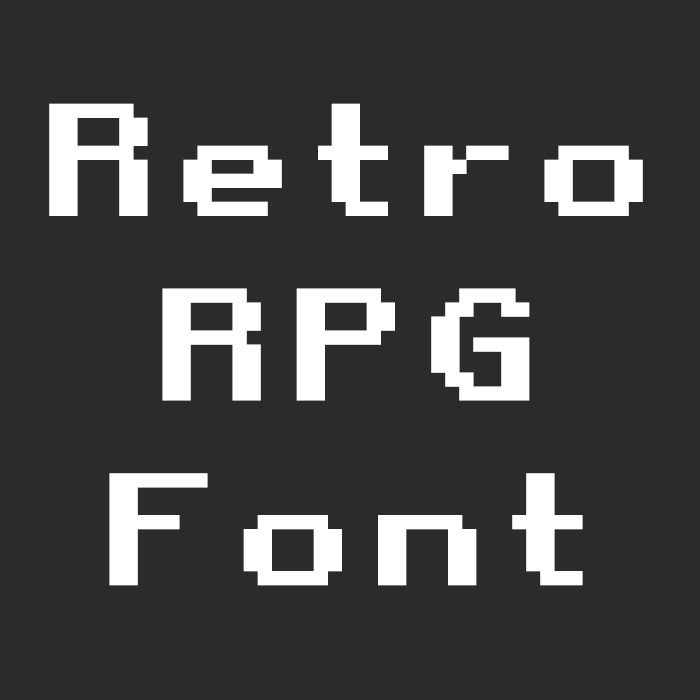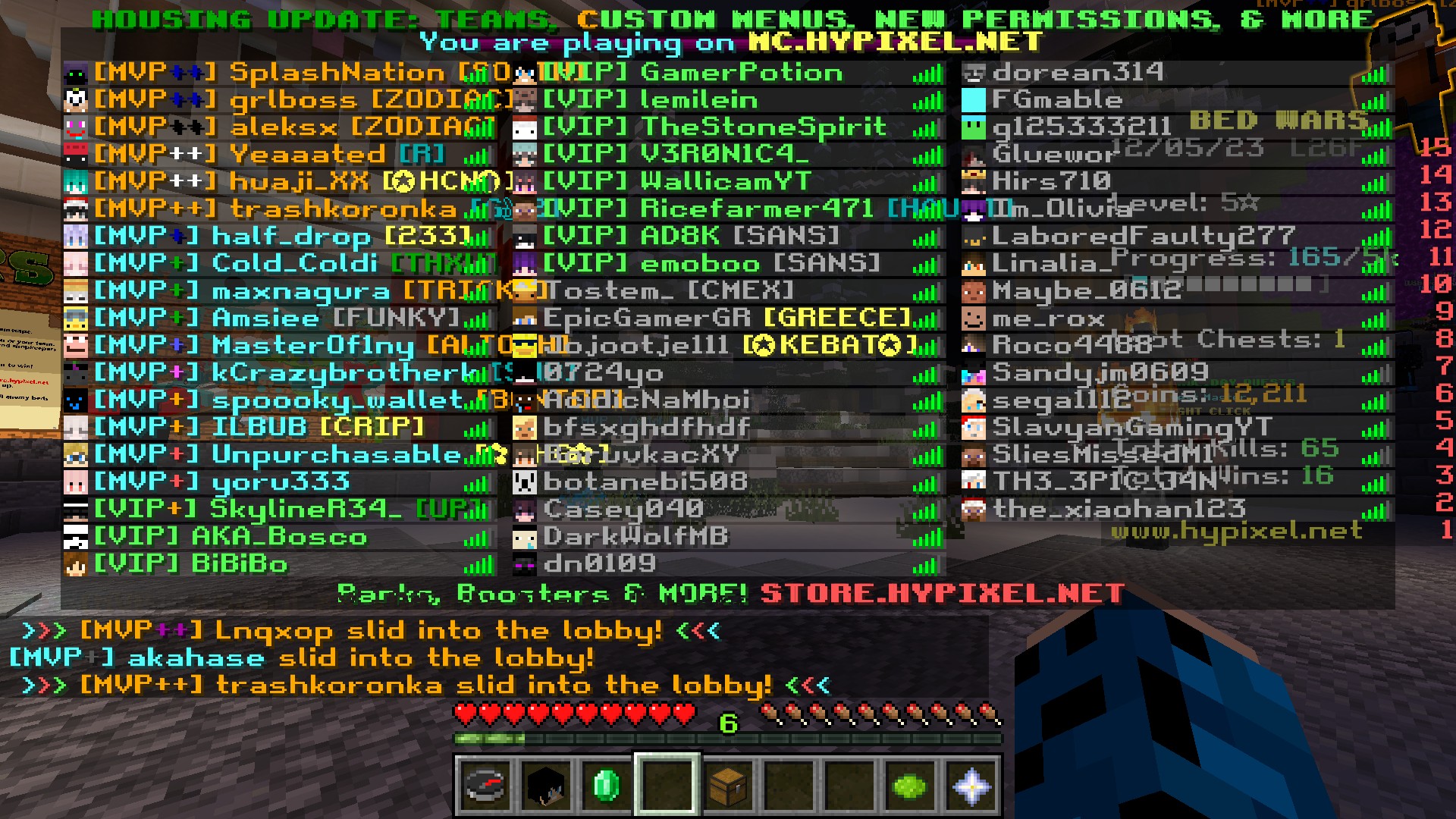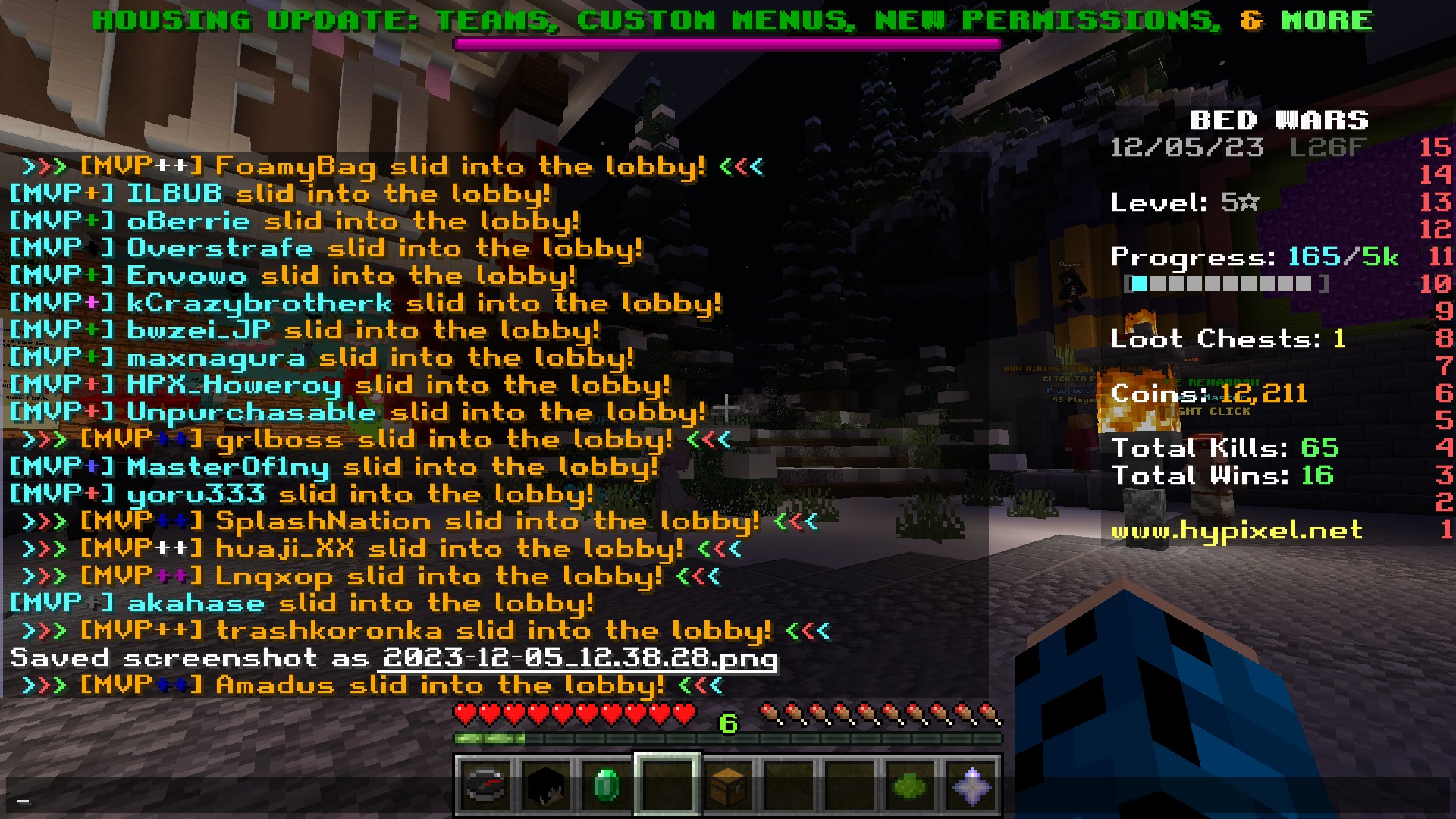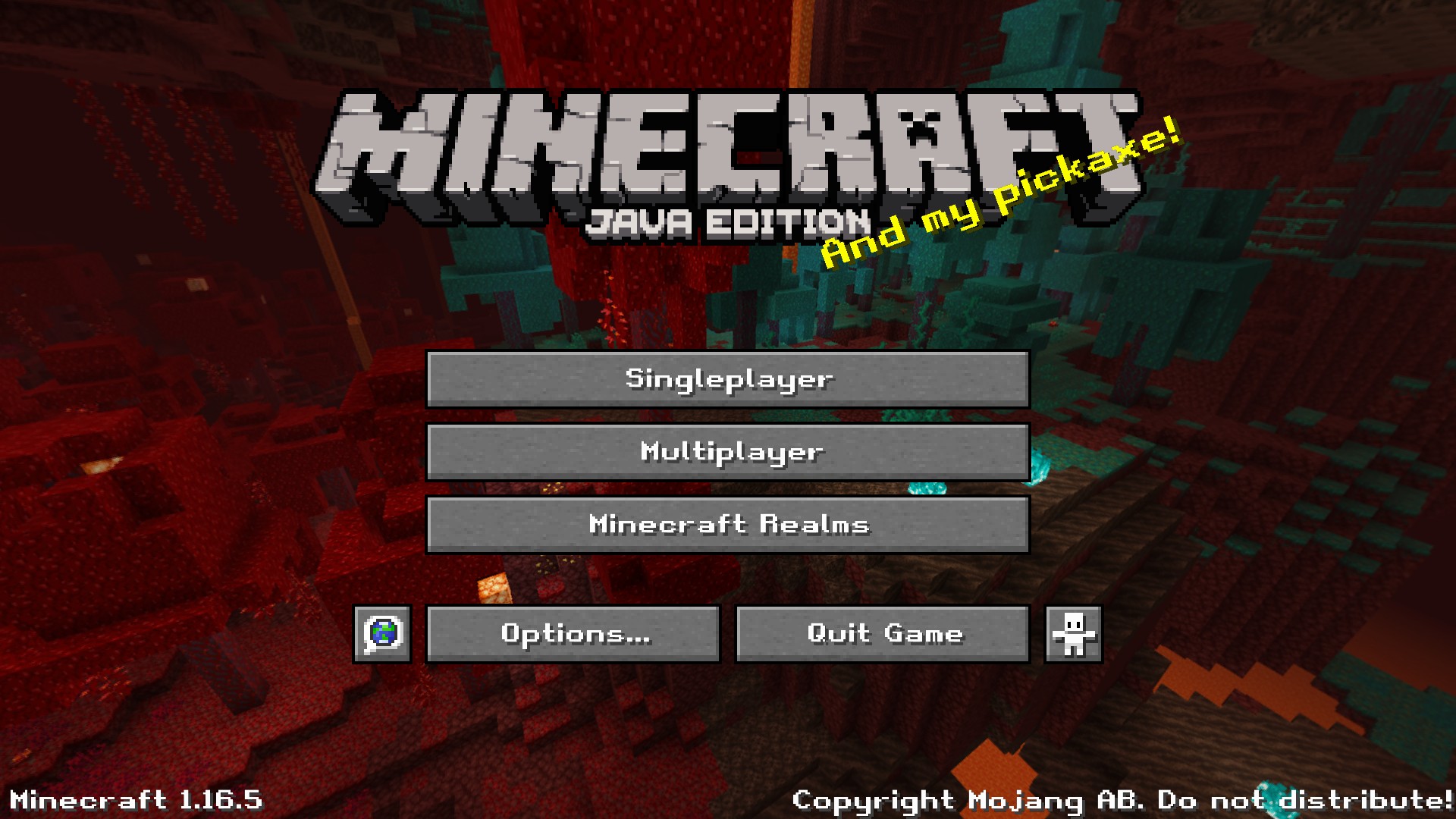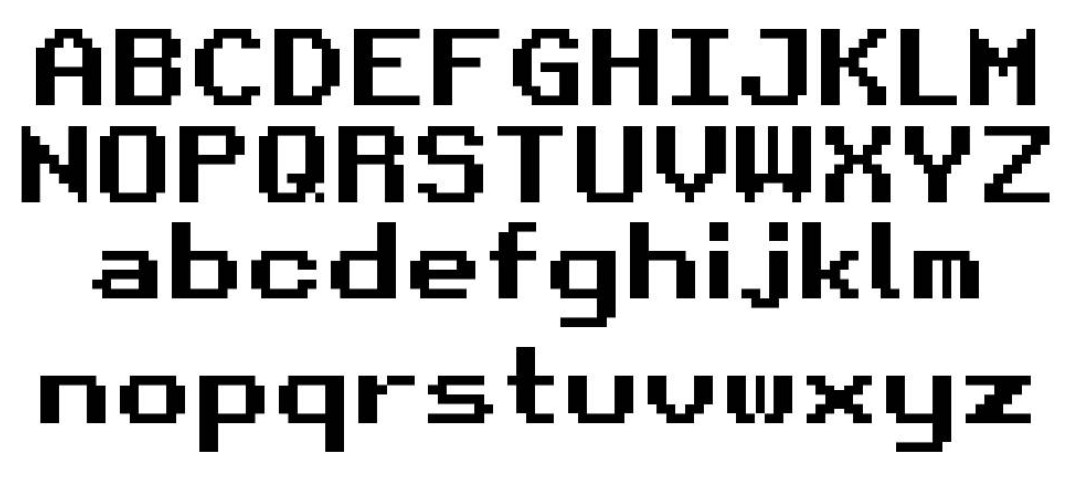
Retro RPG Font
Измените текст в игре с уникальным шрифтом в ретро-стиле.
Погрузитесь в атмосферу уникального игрового процесса с модом Retro RPG Font, который кардинально изменит ваше восприятие текстов в Minecraft! Этот мод добавляет стильный и легко читаемый шрифт в ретро-RPG стиле, что сделает вашу игру не только более приятной, но и удобной. Шрифт был разработан для модпака DarkRPG, но теперь он доступен всем игрокам, стремящимся улучшить свой опыт.
Основные характеристики Retro RPG Font
• Уникальный стиль: Ретро-дизайн шрифта создаёт аутентичную атмосферу классических ролевых игр.
• Читаемость: Специально разработанный для упрощения восприятия текста во время игры.
Не упустите возможность преобразить свою игру с помощью Retro RPG Font! Откройте для себя новый уровень погружения и насладитесь эффектами, которые этот мод может предложить. Присоединяйтесь к тысячам других игроков, которые уже оценили преимущества использования этого шрифта!